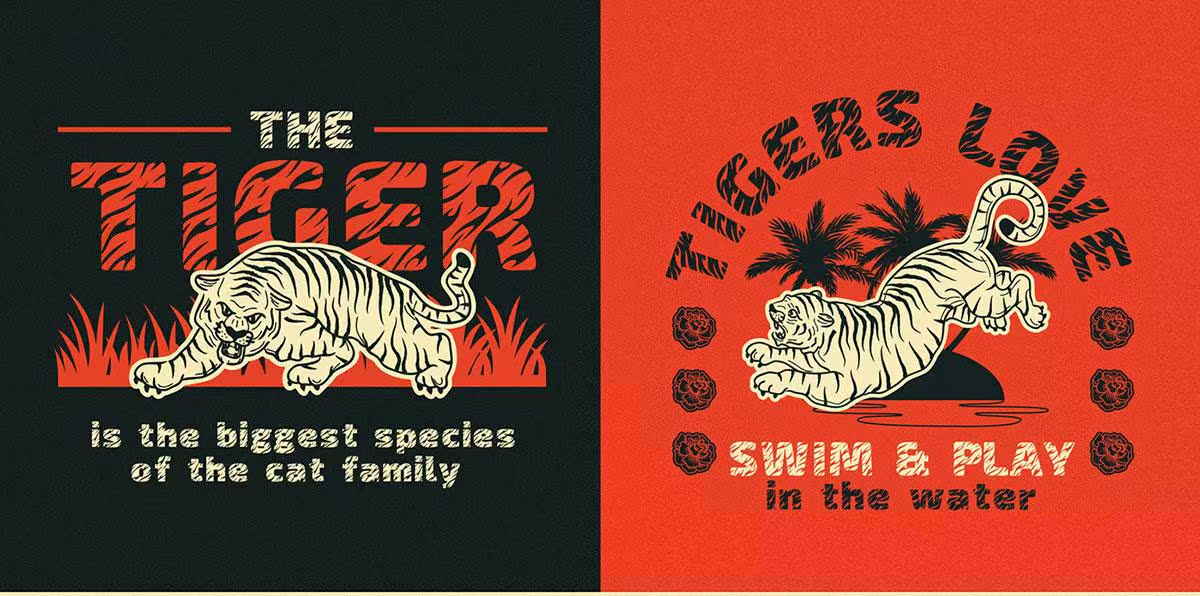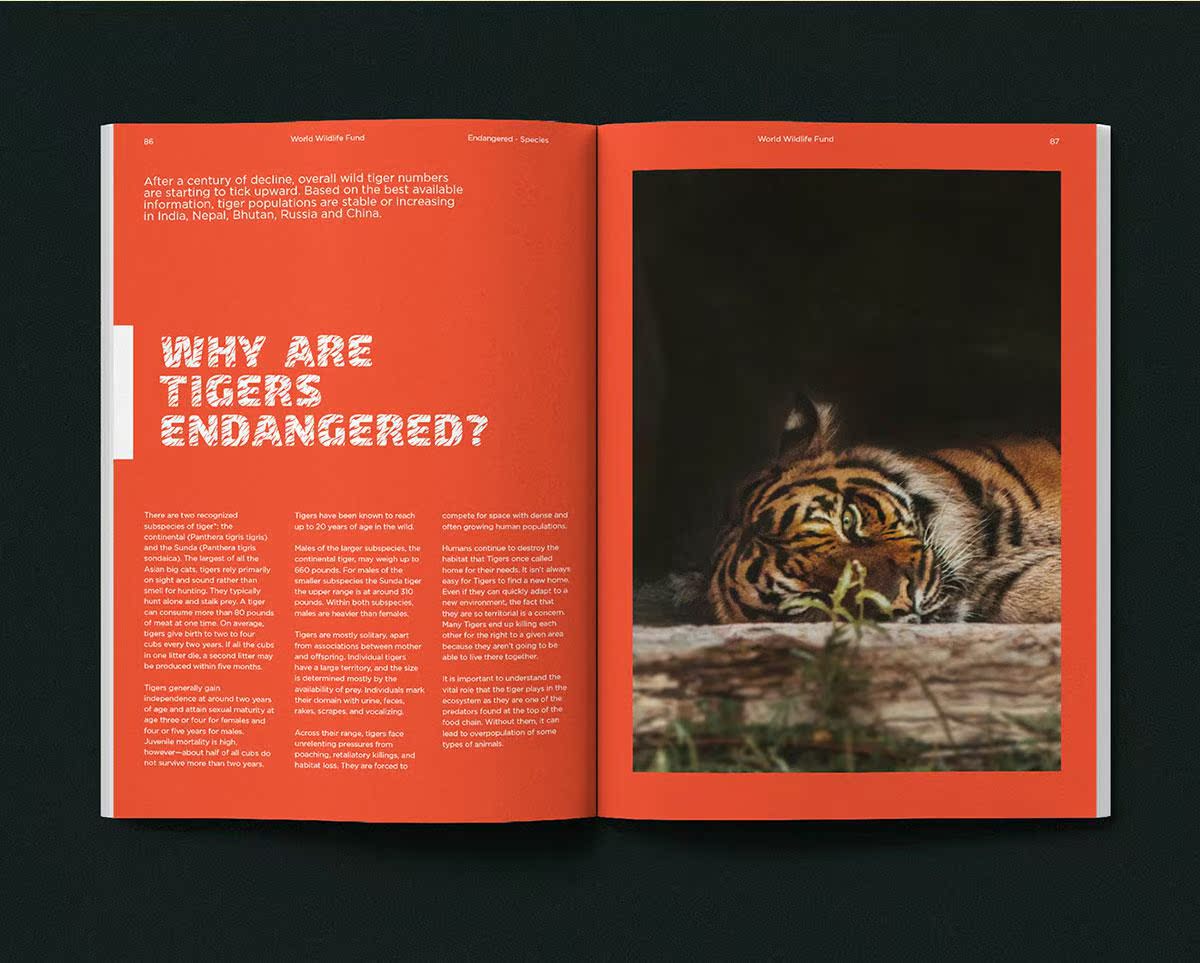
Tigerking Free Display FontIsananimalPrint Texture fromUnotype。对于您下一个设计项目的独特内容的用户,此独特外观的FontIsananimalPrint非常吸引。因此,请立即下载,让您的工作更加精彩!此字体适用于海报、徽标、标题、印刷品和许多字体。